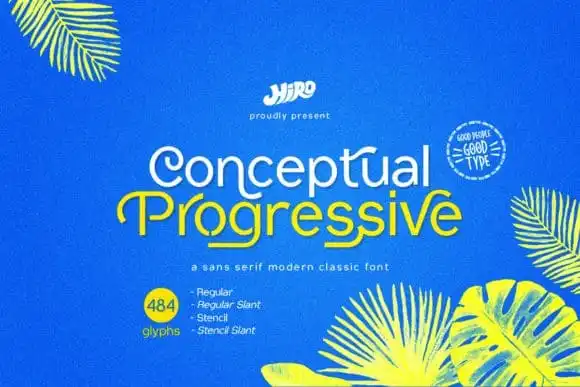
Conceptual Progressive Sans Serif Font – Download Grátis
A Conceptual Progressive Sans Serif Font é uma escolha perfeita para quem busca uma mistura criativa entre elegância e simplicidade. Sua aparência minimalista mas sofisticada a torna ideal para um vasto conjunto de projetos gráficos, seja em desenhos digitais coloridos ou em designs tradicionais que valorizam o estilo serifado. Esta fonte foi desenvolvida por HIRO.std e é conhecida por sua simplicidade, mas também por seu charme elegante. Suas linhas leves e bem definidas a tornam uma opção confiável para qualquer ocasião ou projeto, garantindo um visual atraente que se assemelha às letras de escrita serifada convencional. É ideal tanto para publicar versões tradicionais quanto para incorporar em projetos digitais coloridos, fazendo dela uma fonte versátil e irresistível.